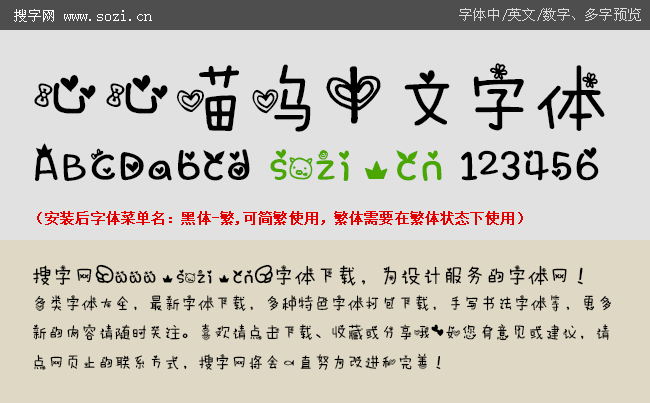
心心喵嗚中文字體
搜字網(wǎng)給大家提供一款很卡通的手機中文字體下載。修改者將它命名為心心喵嗚中文字體,這款手機字體是以方正喵嗚體為原形,字體的一些筆畫替換成了非常有趣的卡通心形圖案,方正喵嗚體是少女漫畫家喵嗚聯(lián)手方正出品的一款手寫涂鴉字體,字形活潑、可愛、隨意,給人一種無憂無慮毫無約束的自由之感。特別適合喜歡手機字體個性一些的朋友在手機上安裝使用。